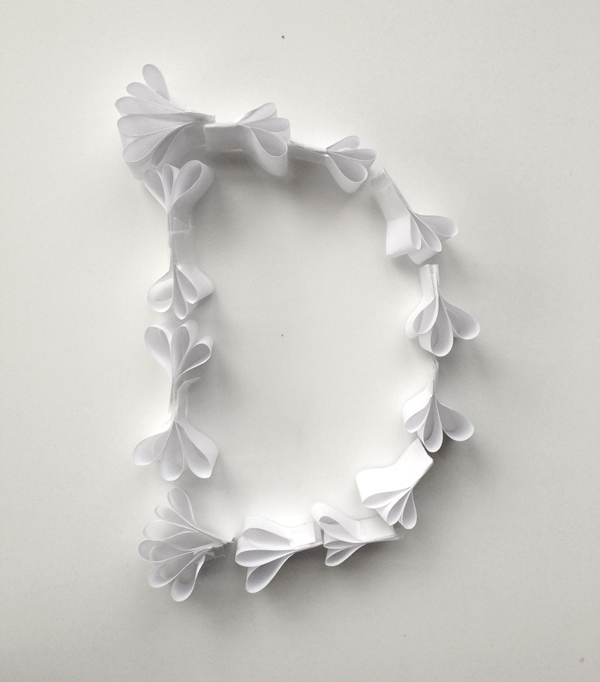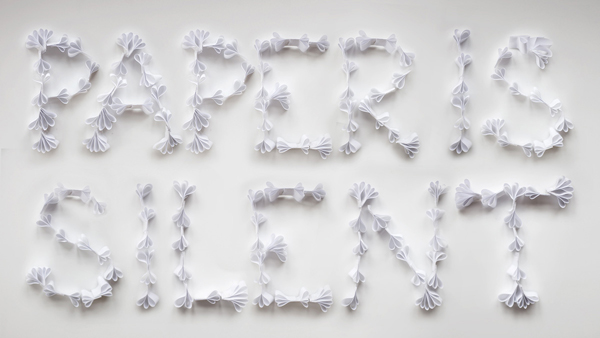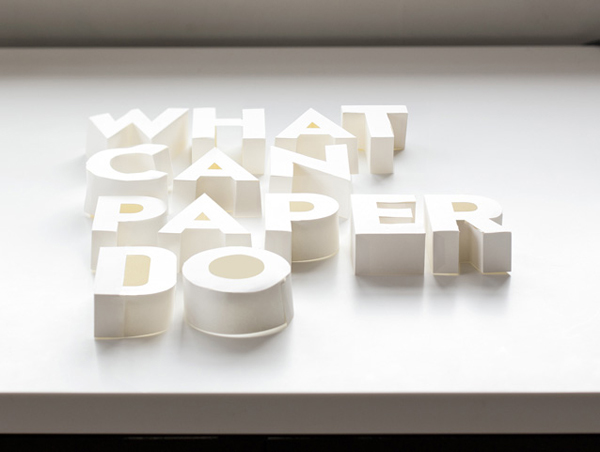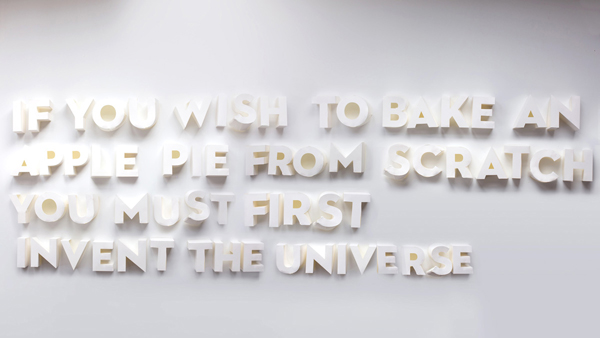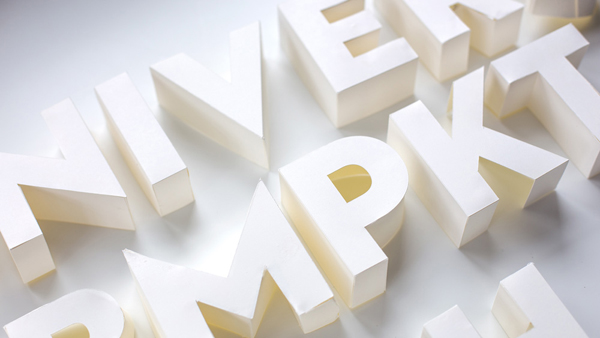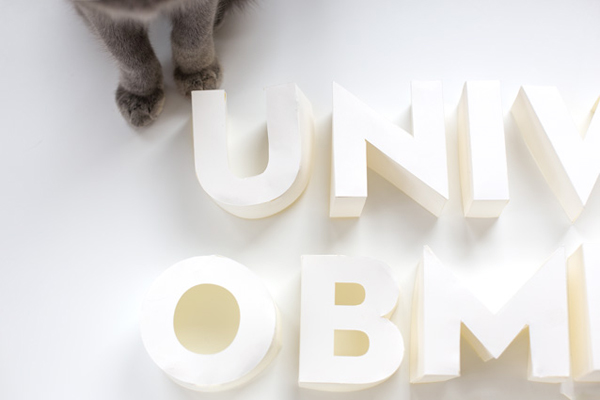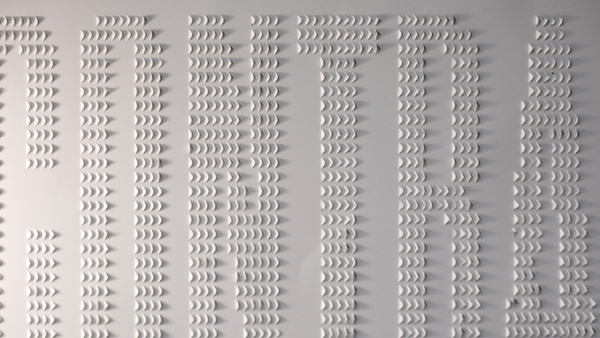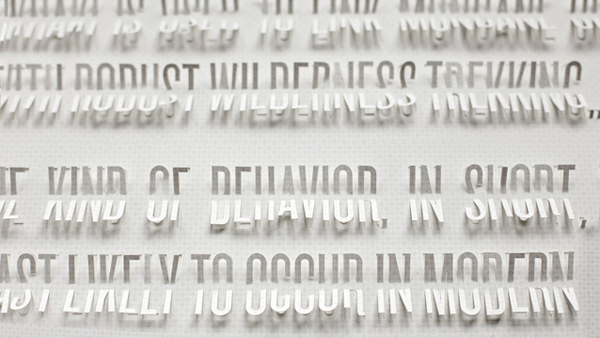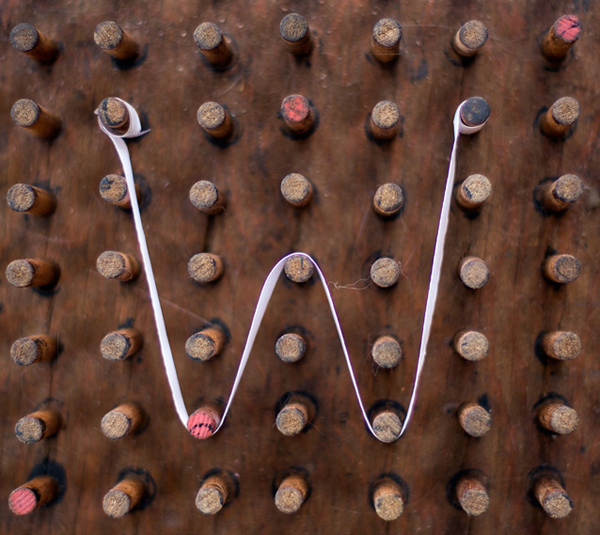
El pasado 12 de abri Kelli Anderson impartió una conferencia en el TYPO International Design Talks de San Francisco donde presentó su trabajo Paper Type Experiments. El encuentro, organizado bajo el lema Compare and contrast, acogió su propuesta sobre el uso del papel no como soporte de la tinta sino como elemento físico que da forma a la letra. Hechas en papel, las palabras juegan con el contraste de volumen y luz para sorprender al espectador con sus inesperadas tipologías.
Paper Type Experiments, Kelli Anderson, 2013.
A la diseñadora gráfica y artista americana le interesa crear objetos para la vida diaria y descubrir cómo las personas pueden interactuar con ellos. Su trabajo se extiende desde las cubiertas de libros hasta logotipos para aplicaciones y mapas. Busca llevar al límite de lo ordinario los materiales y los formatos, sacar a la luz secretas posibilidades. Con Paper Type Experiments ha querido forzar a sus espectadores a mirar y descubrir. Rotas sus expectativas, se ven sorprendidos por las inadvertidas formas y matices que toman las palabras.
Paper Type Experiments, Kelli Anderson, 2013.
Cada una de las letras ha sido cortada, doblada y compuesta de manera individual. Sus diseños con reminiscencias florales, hechos a partir de tiras de papel sucesivamente plegadas en elementos lobulados, se contraponen a las tipologías de volumen más definido.
Paper Type Experiments, Kelli Anderson, 2013.
La luz recorta sus límites, rotundos o imprecisos, al tiempo que dota a las palabras de otra nueva vida. Adquieren una plasticidad que se revela poco a poco por el efecto del contraste. El tiempo, el antes y el después de sus composiciones móviles, o el claroscuro, lo que queda en la sombra y lo que es iluminado, provocan ese cambio que busca la diseñadora.
Paper Type Experiments, Kelli Anderson, 2013.
Los formatos tradicionales son ligeramente alterados para mostrar algo más de lo que intuimos por primera vez. Sus diseños fluyen e indagan sobre lo que está en continuo cambio. Con ellos pretende forzar a sus espectadores a dejar atrás ciertas creencias preconcebidas para experimentar y descubrir la presencia física de las palabras.
Paper Type Experiments, Kelli Anderson, 2013.